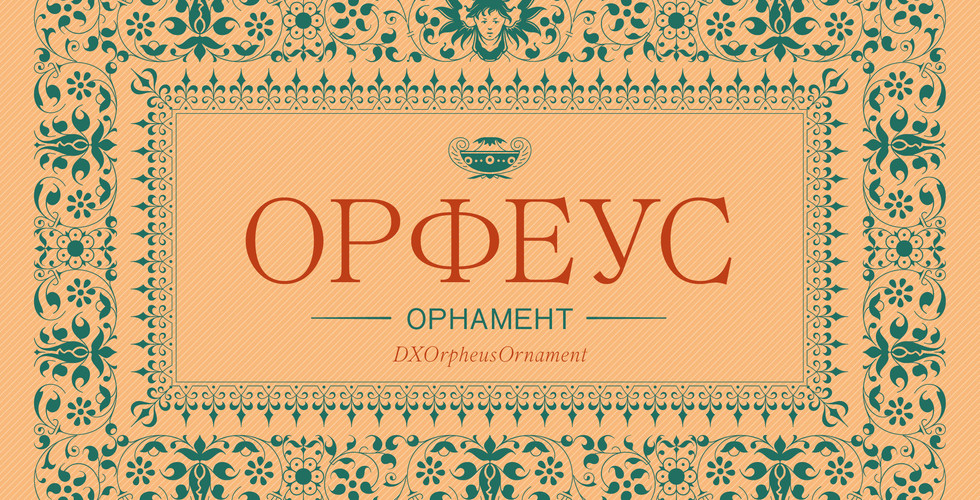
Орнамент Орфеус/DXOrpheusOrnament22 окт. 2016 г.1 мин. чтенияВыпущен орнамент Орфеус/DXOrpheusOrnament, воссозданный на основе рисунка "Орнамента №24" из каталога Словолитни О.И.Лемана за 1914 год.#дореволюционный #русский #Орнамент #DXOrpheusOrnament #Орфеус